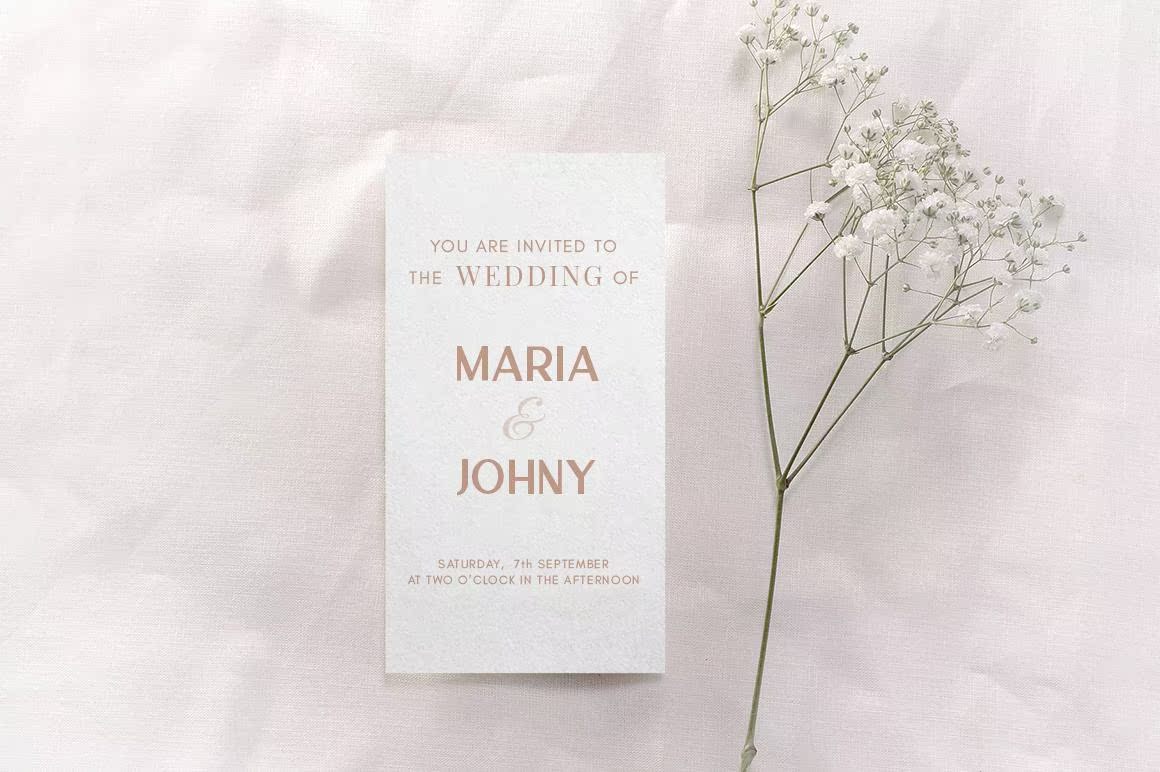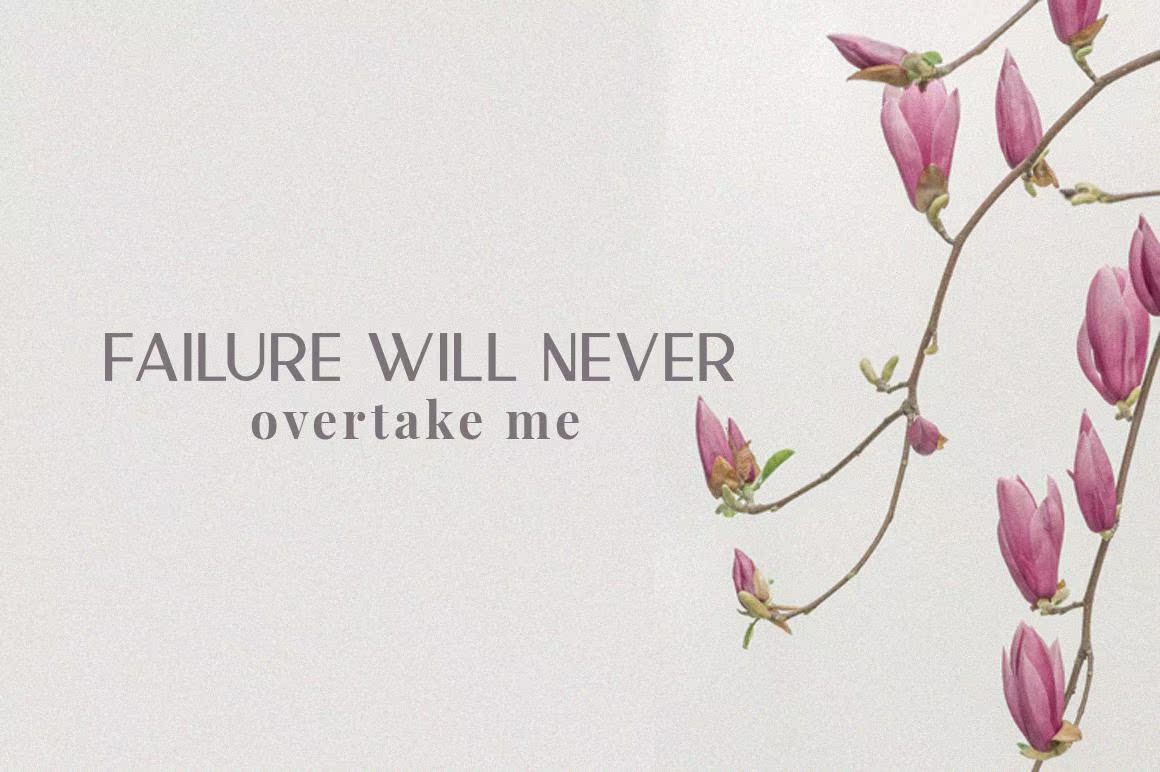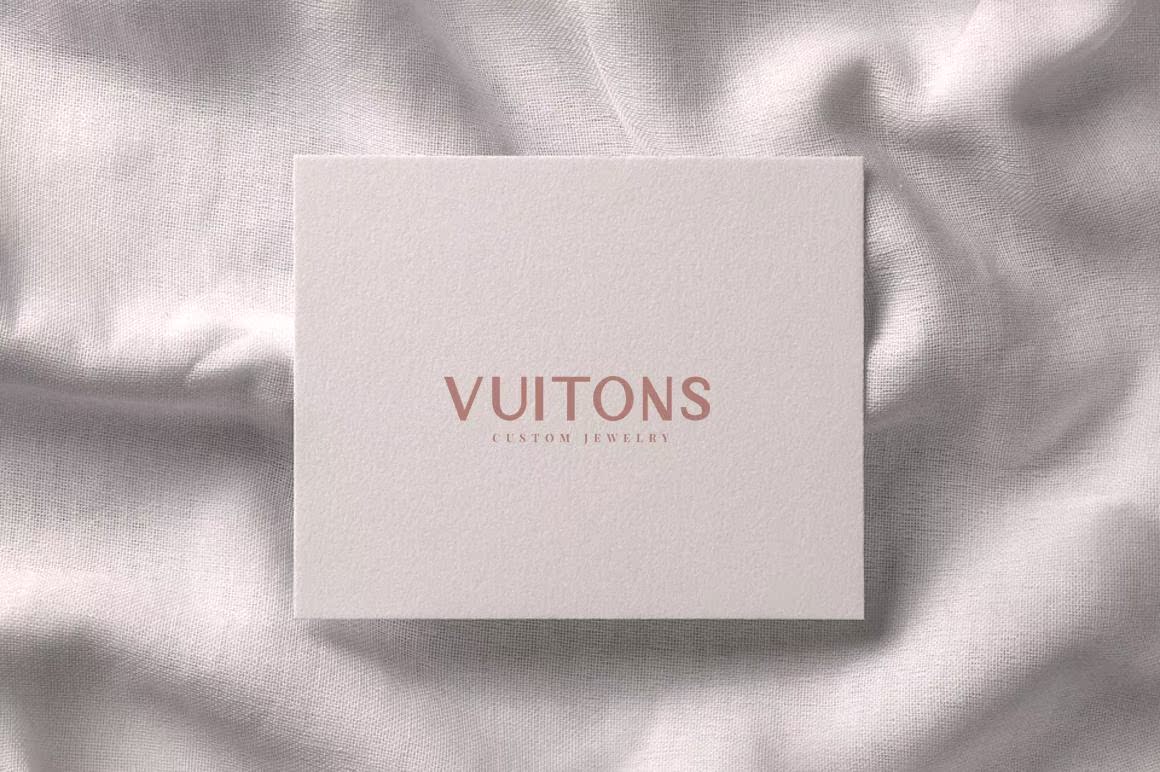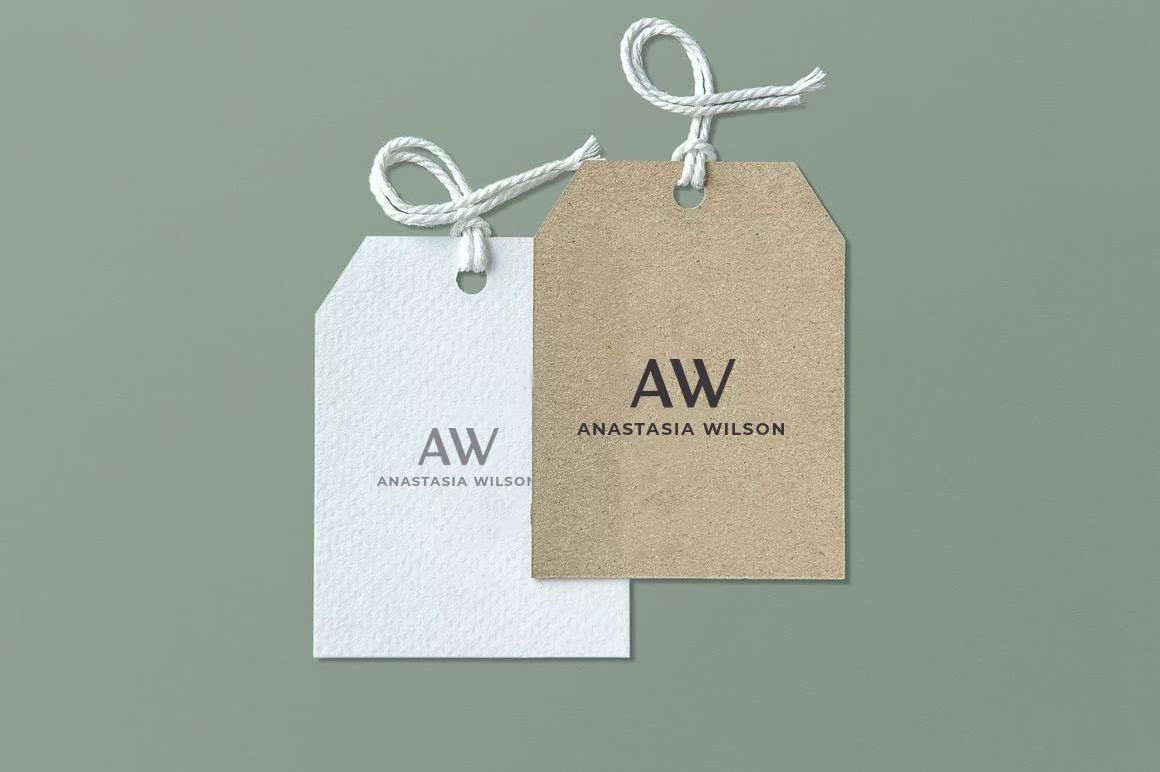
FreeCremonaMinimalSanserifisAbeAutifulsAnsfont具有强大的特性。它为您的项目寻找专业。尽管如此,它将使您的设计具有强大的完整性。因此,它非常适合于演示、名片、杂志、横幅、,和更多。此演示文稿可用于两种格式文件,而Charett Fan不支持您在设备上安装和下载的格式文件。此外,它也可用于常规、粗体和塔利克。但是,它是个人许可使用的,但如果您想获得更多功能,请购买预版本。